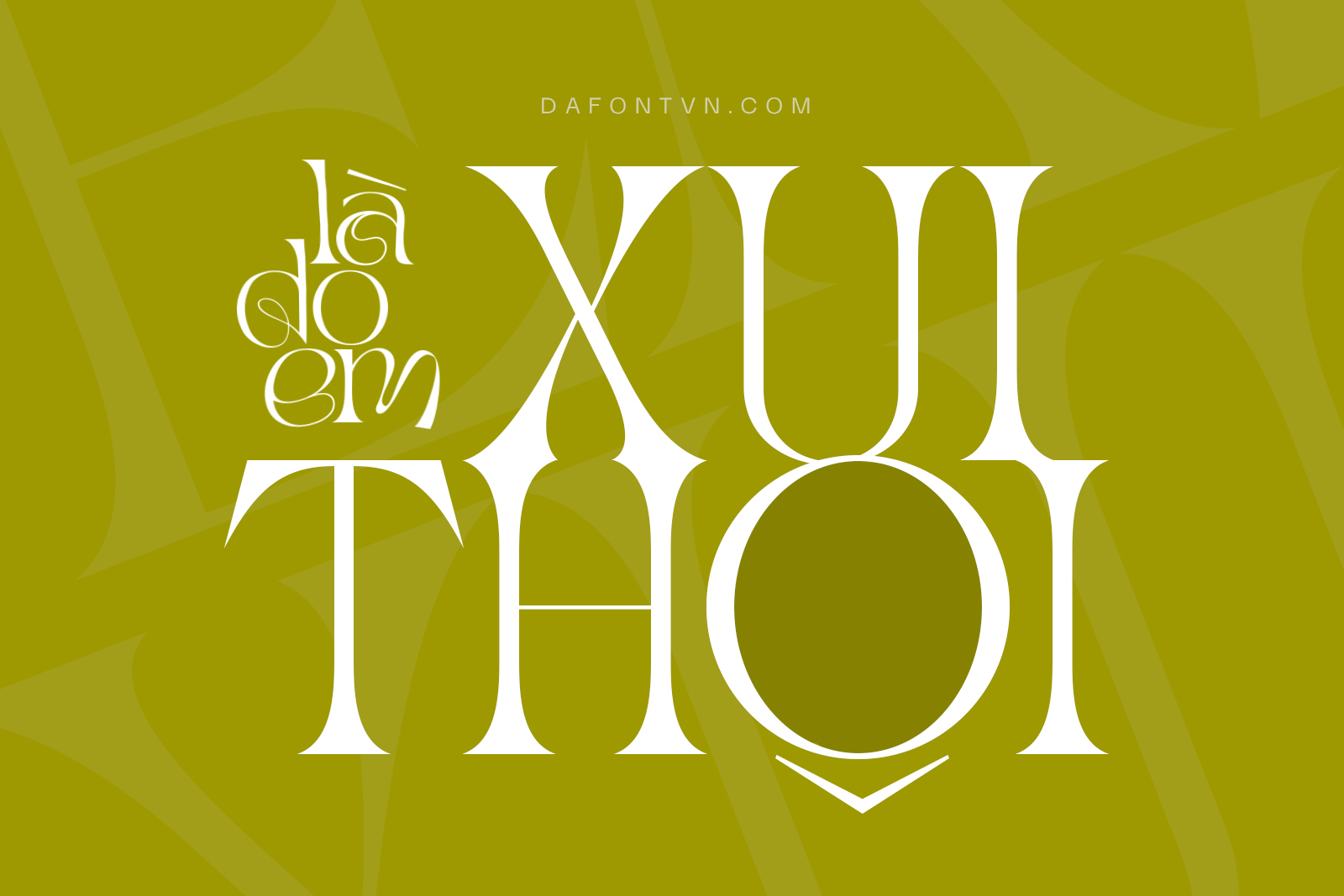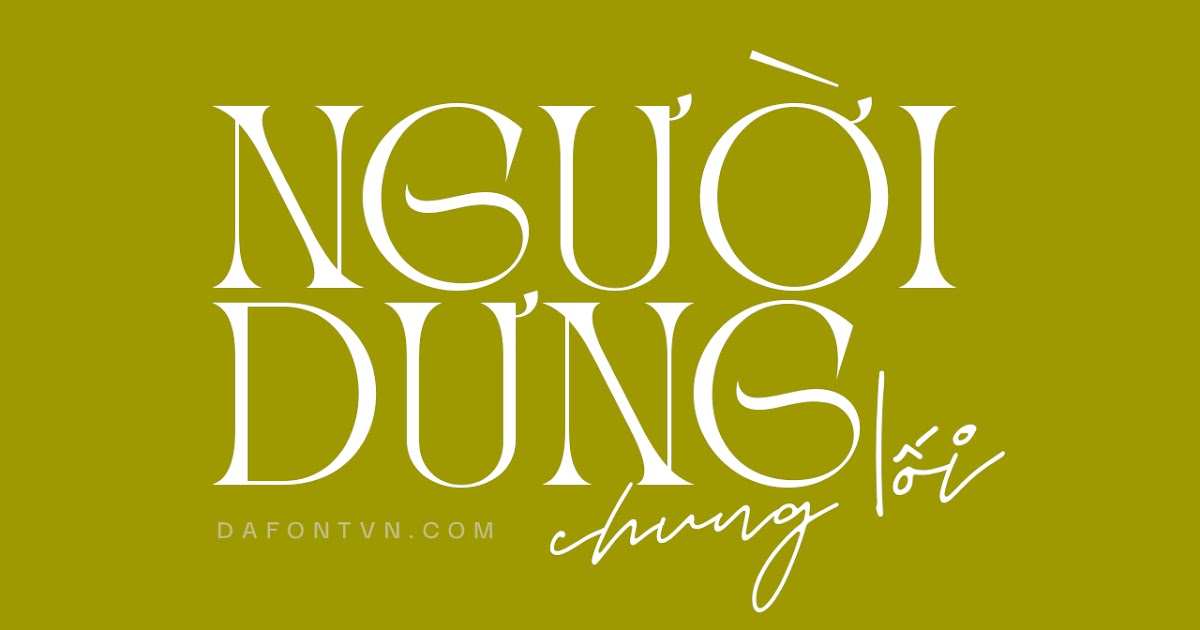
Font Lagmaq Việt hóa – 1 kiểu font rất độc đáo
Lagmaq Font – 1 kiểu font mang phong cách gothic cổ điển nhưng lại rất hiện đại.
Font serif Lagmaq lấy cảm hứng từ phong cách gothic với các nét chữ được thiết kế rất độc đáo, ấn tượng, nghệ thuật và hiện đại vì vậy nếu bạn đang cần 1 font chữ lạ mắt độc lạ thì đây là 1 kiểu font rất tốt cho các dự án của bạn. Font chữ phù hợp cho nhiều thiết kế khác nhau như poster, typography, quảng cáo, thời trang, thiệp mời, logo, tiêu đề…
Đặc biệt font Lagmaq đi kèm với nhiều ký tự thay thế và rất nhiều chữ ghép đẹp mắt để bạn có thể tạo ra các thiết kế phá cách hơn. Font được việt hóa rất cẩn thận, căn chỉnh các dấu, kerning các ký tự tiếng Việt và được mã hóa PUA.